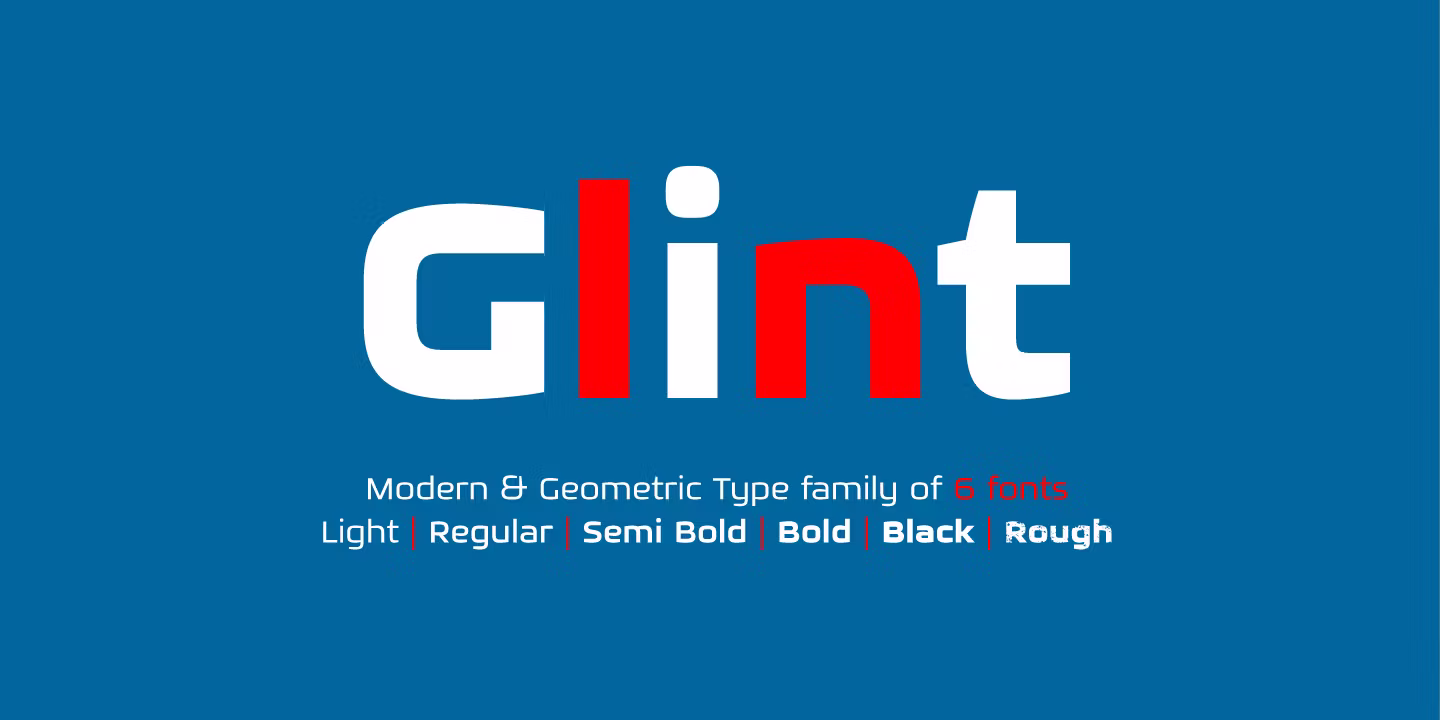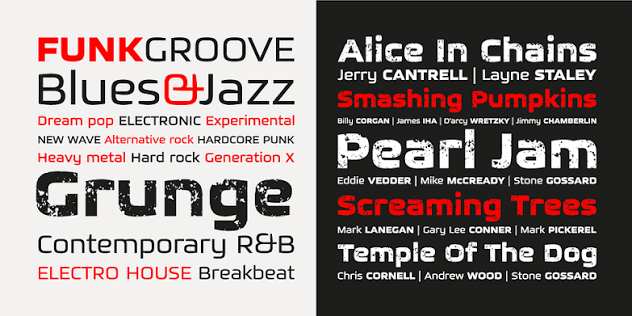
Font Glint Việt hóa là bộ phông chữ thuộc dòng Modern Display mang phong cách tối giản, sắc sảo và tràn đầy nét thanh lịch đương đại. Với cấu trúc hình học chuẩn xác kết hợp cùng những đường cắt vát tinh tế ở các đầu nét, phông chữ này toát lên vẻ đẹp kiêu sa, thời thượng, cực kỳ thích hợp cho các thiết kế logo thời trang xa xỉ, nhãn chai nước hoa, bìa tạp chí và bao bì mỹ phẩm cao cấp. Doozypack.vn cung cấp link Glint Font Download chuẩn kỹ thuật, giúp bạn sở hữu phông chữ đẳng cấp này mà không lo gặp bất kỳ lỗi hiển thị dấu thanh nào khi thiết kế in ấn.
Đặc điểm thẩm mỹ độc đáo của bộ font Glint
Glint không đi theo sự phô trương rườm rà; nó mang đến một ngôn ngữ thị giác đầy tính tối giản (Minimalism) nhưng vô cùng sắc lẹm, tạo ấn tượng sâu sắc nhờ sự tinh tế trong từng tỷ lệ hình khối.
Phong cách Modern Display sắc sảo và thanh lịch
Đặc trưng lớn nhất của Font Glint Việt hóa là sự cân bằng tuyệt đối giữa các đường thẳng dứt khoát và tỷ lệ x-height thoáng đãng. Cấu trúc chữ sở hữu độ tương phản nét thanh đậm vừa phải, các điểm giao nét được vát góc nhẹ nhàng tạo nên cảm giác lấp lánh (như tên gọi “Glint” – lóe sáng) dưới ánh đèn. Khi đặt Glint làm tiêu đề trên bao bì, thương hiệu của bạn sẽ ngay lập tức toát lên vẻ ngoài đắt tiền, uy tín và mang đậm tinh thần của các kinh đô thời trang lớn.
Cấu trúc chữ tối giản với những đường cắt vát tinh tế
Các ký tự của Glint Bold Font Free Download sở hữu độ dày dặn vững chãi nhưng vẫn giữ được sự thanh thoát cần thiết. Sự kết hợp này giúp tiêu đề bản thiết kế giữ được sự đĩnh đạc, hiện đại và không hề gây cảm giác nặng nề, rất phù hợp với các mẫu hộp giấy định vị ở phân khúc thượng lưu.
Ưu điểm nổi bật của bản Font Glint Việt hóa
Khi ứng dụng các phông chữ tối giản sắc sảo vào thị trường trong nước, sự chỉn chu về dấu câu là yếu tố quyết định đến tính chuyên nghiệp của bản thiết kế:
- Khắc phục triệt để lỗi dấu tiếng Việt: Phiên bản Việt hóa đã được đội ngũ thiết kế trau chuốt thủ công từng dấu câu. Các dấu sắc, huyền, hỏi, ngã, nặng được vẽ với tỷ lệ cân đối, đặt ở vị trí thoáng đãng so với thân chữ, không gây cảm giác chắp vá hay làm đè nét làm mất tính thẩm mỹ tối giản.
03 Ứng dụng thực tế của font Glint trong sản xuất bao bì tại Doozypack.vn
Sự sắc sảo và thanh lịch của Glint mang lại hiệu ứng thị giác đắt giá trên các dòng sản phẩm bao bì thực tế do Doozypack.vn sản xuất:
- Hộp giấy đựng Nước hoa & Mỹ phẩm Luxury: Tiêu đề thương hiệu in bằng font Glint kết hợp kỹ thuật ép kim nhũ bạc (Silver Stamping) trên nền hộp đen nhám tạo nên vẻ đẹp sang trọng chuẩn phong cách thời trang cao cấp.
- Túi giấy thời trang cao cấp: Tên cửa hàng in bằng font Glint màu đen tối giản trên nền túi giấy Ivory trắng giúp khẳng định gu thẩm mỹ tinh tế và hiện đại của nhãn hàng.
- Nhãn dán chai Tinh dầu & Nến thơm: Nét chữ hình học tinh tế mang lại cảm giác thư giãn, sạch sẽ và thượng lưu cho các dòng sản phẩm quà tặng tinh tế.
Lưu ý kỹ thuật khi in ấn với phông chữ sắc sảo Glint
- Kiểm soát độ dày nét khi in kích thước nhỏ: Các đường cắt vát của font Glint có độ mảnh vừa phải. Khi in trên giấy Kraft thô nhám, bạn nên để size chữ tiêu đề tối thiểu từ 8pt trở lên để bảo đảm độ rõ nét của các ký tự.
- Lựa chọn hệ màu sắc tối giản: Phong cách Glint đẹp nhất khi phối cùng các tông màu đơn sắc (Đen, Trắng, Xám) hoặc kết hợp kỹ thuật ép kim kim loại. Sự tối giản này sẽ tôn vinh trọn vẹn hình khối sắc sảo của phông chữ.